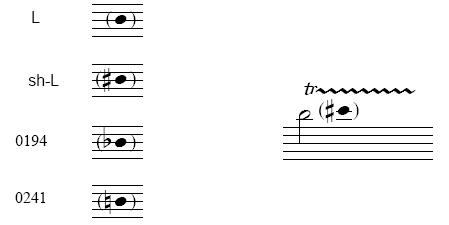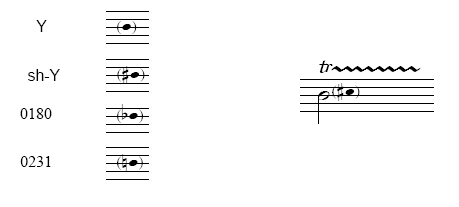
Set uno: Dimensione intera
Queste teste di note consentono di agevolare l’indicazione della nota su cui trillare specialmente quando queste si trovano al di fuori del rigo. Per prima cosa dovete inserire la nota utilizzando uno dei metodi di Finale, quindi dovete cambiare la testa della nota utilizzando lo Strumento Speciale per cambiare la testa delle note, accorciare il gambo e spostarla nella posizione orizzontale desiderata.
Set Due: riduzione del 75%
Queste teste di note sono già ridotte del 75% e possono essere usate per indicare la nota su cui trillare all’interno del pentagramma. Inseritele in partitura con lo Strumento Articolazioni.